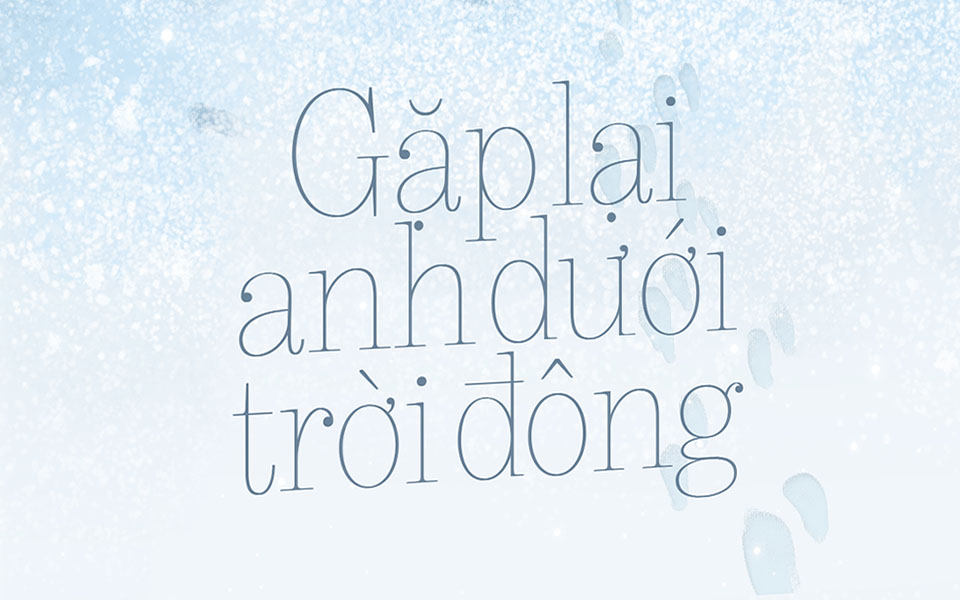
Giới thiệu về bộ Font việt hoá MTD 21 Cent
Trong lĩnh vực thiết kế đồ họa học đường, việc lựa chọn một bộ Font Chữ phù hợp đóng vai trò quan trọng trong việc truyền tải kiến thức. Font việt hoá MTD 21 Cent là một phiên bản đặc biệt được tinh chỉnh để phục vụ cộng đồng thiết kế tại Việt Nam. Với phong cách thanh lịch và hiện đại, bộ font này giúp các bài giảng, báo tường hay tài liệu học tập trở nên sinh động và chuyên nghiệp hơn rất nhiều. Khả năng hiển thị tiếng Việt hoàn hảo, không lỗi dấu chính là ưu điểm lớn nhất của nó.
Đặc điểm nổi bật của Font việt hoá MTD 21 Cent
Nét chữ thanh thoát và dễ đọc
Font việt hoá MTD 21 Cent sở hữu các đường nét tròn trịa nhưng vẫn giữ được sự ngay ngắn cần thiết. Điều này giúp học sinh dễ dàng tiếp nhận thông tin trên các slide trình chiếu hoặc poster thông báo. Độ tương phản giữa các nét thanh và nét đậm được xử lý tinh tế, tạo cảm giác dễ chịu cho mắt khi phải đọc các đoạn văn bản dài trong thời gian học tập liên tục.
Ứng dụng đa dạng trong nhà trường
Không chỉ dùng cho văn bản, bộ font này còn cực kỳ hiệu quả khi áp dụng vào các tiêu đề bìa sách, nhãn vở hay các ấn phẩm truyền thông của nhà trường. Sự linh hoạt của nó cho phép người dùng sáng tạo không giới hạn, từ phong cách cổ điển đến tối giản. Bạn có thể kết hợp font này với nhiều tông màu khác nhau để tạo nên những sản phẩm hình ảnh ấn tượng, mang đậm dấu ấn cá nhân và tập thể.